“见字如晤”这四个字最好的解答了清秀字体魅力到底在哪里的疑惑, 因为字体本身就是充满了无穷无尽的魅力的,它可以说是文化与想象力的缔造者。大家可以试想下当你在读一篇用着清秀字体的 字体图片 或者书信、文章时,脑海里浮现的画面可以是一位清秀灵动,笑靥如花的妙龄少女,也可以是气质温润的翩翩少年,清秀的字体给人一种清新自然、、如沐春风,心旷神怡的感受。
不如大家跟小编一起来探探这令人如沐春风的清秀字体的究竟吧!
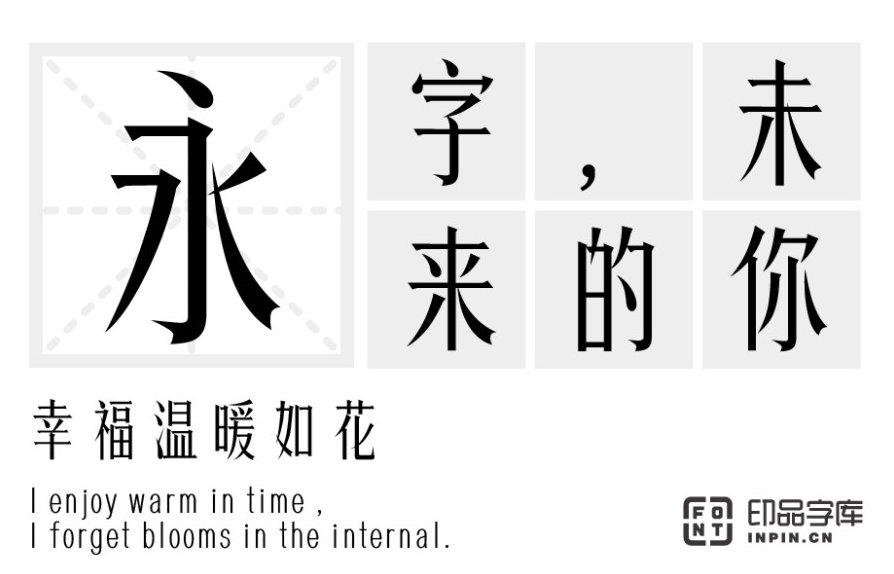
印品清秀体:这款字体用一个词语来形容就是:清秀。跟设计师给它取的名字一样,气质娟秀,清雅悦目,拥有秀明的个性,自行工整修长、细节飘逸。在笔画上的处理更加细致,整体看起来舒服易于阅读,非常适用于带有清和雅致风格的标题和正文排版;
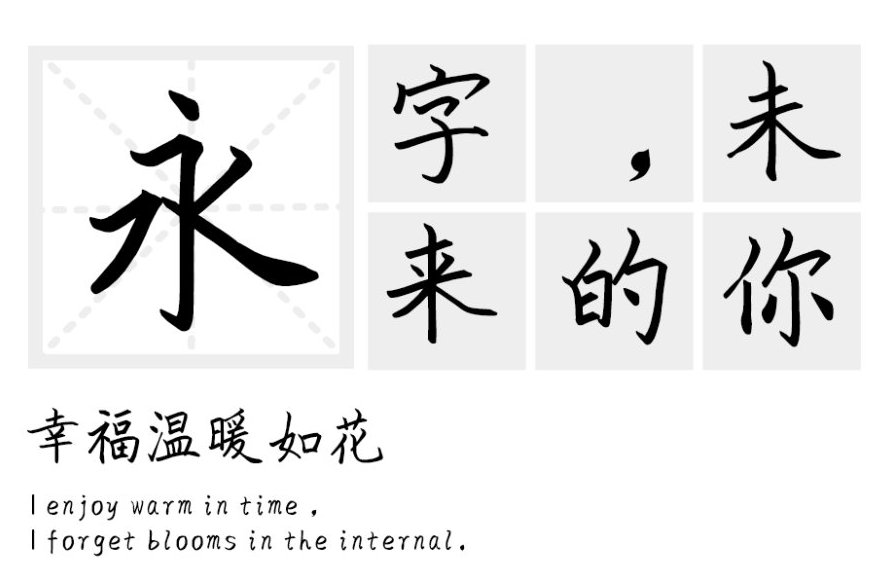
汉标精工闺蜜楷体:这款字体衍生与传统的书法字体,在笔画和结构上保留的一定的传统书法特征,延续了传统书法的韵味,同事采用了更大的中宫,使得它隽秀、淡雅工整,观看图片时更可以一目了然的 字体识别 ,充满韵律丰富的阅读感。这款字体用在文艺类的书刊或者是品牌广告和产品包装设计以及社交网络的个性化用字上都非常合适。